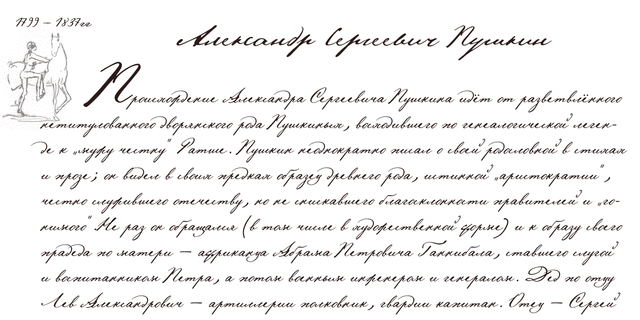
Серия шрифтов 'Пушкин' разработана для фирмы ПараТайп в 1999-2004 годах (дизайнер Геннадий Фридман). Шрифт создан на основе автографов А.С. Пушкина. В комплект знаков шрифта включены альтернативные варианты некоторых букв, характерные для почерка поэта. Шрифт Пушкин Скрипт в двух начертаниях основан на рукописях 1815 года и содержит комплект знаков для набора помимо русского на основных западноевропейских языках. Пушкин Один создан на основе наиболее аккуратно написанных документов. Пушкин Два имитирует вариант мелкого, но тем не менее достаточно разборчивого почерка. Пушкин Три также имеет 2 начертания разных насыщенностей и имитирует автографы, отличающиеся размашистым написанием букв. Шрифты серии Пушкин 1, 2, 3 содержат только буквы русского алфавита. В дополнение к ним спроектирован шрифт Пушкин Франс в западноевропейской комплектации.
Ассоциации c начертанием Pushkin Script LowКачества и характер:
эмоциональный, темпераментный, чувственный, вдохновенный, поэтический, лирический, лихой, неряшливый, быстрый, динамичный, свободный, оригинальный, нервный, колоритный, артистичный, характерный, живой, исторический, страстный, творческий, осенний, стремительный, проворный, вернакулярный, неформальный, бегущий, размашистый